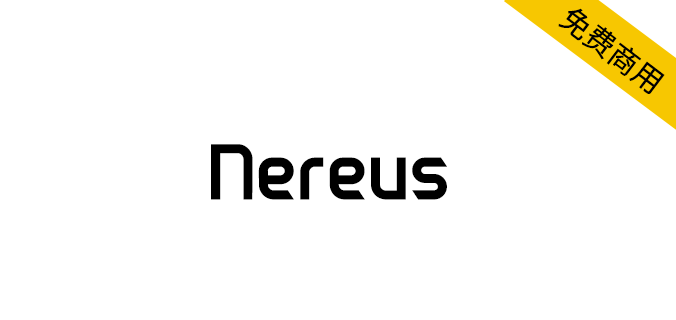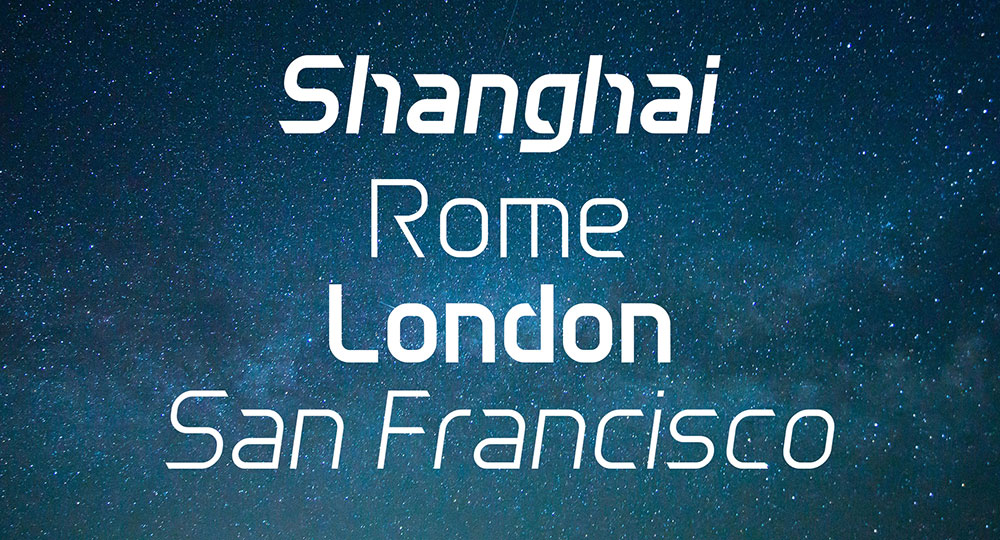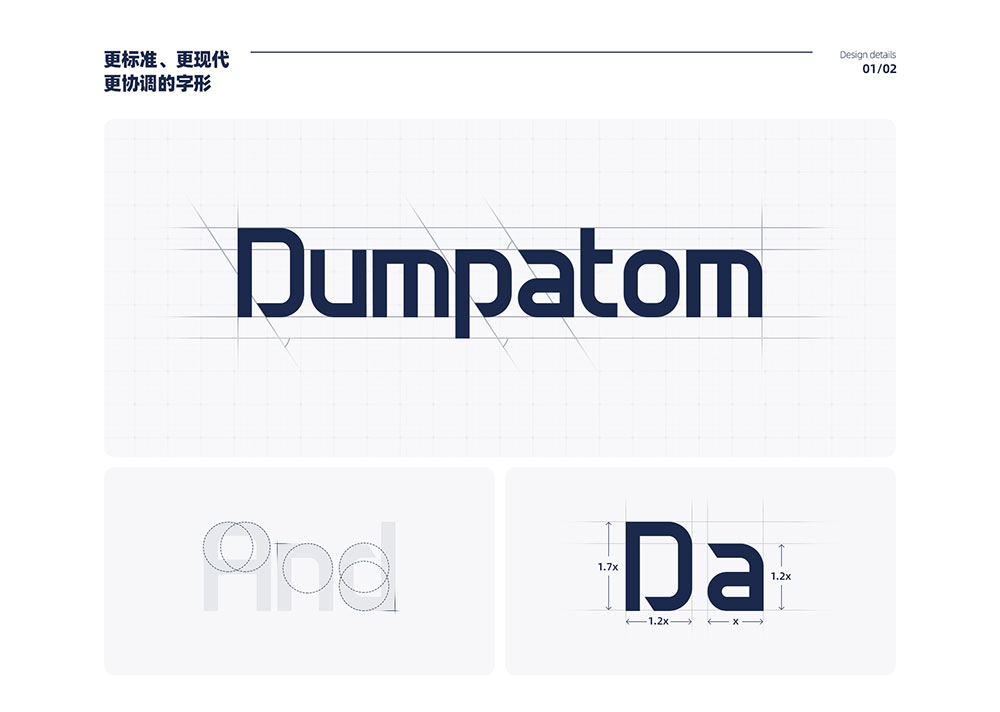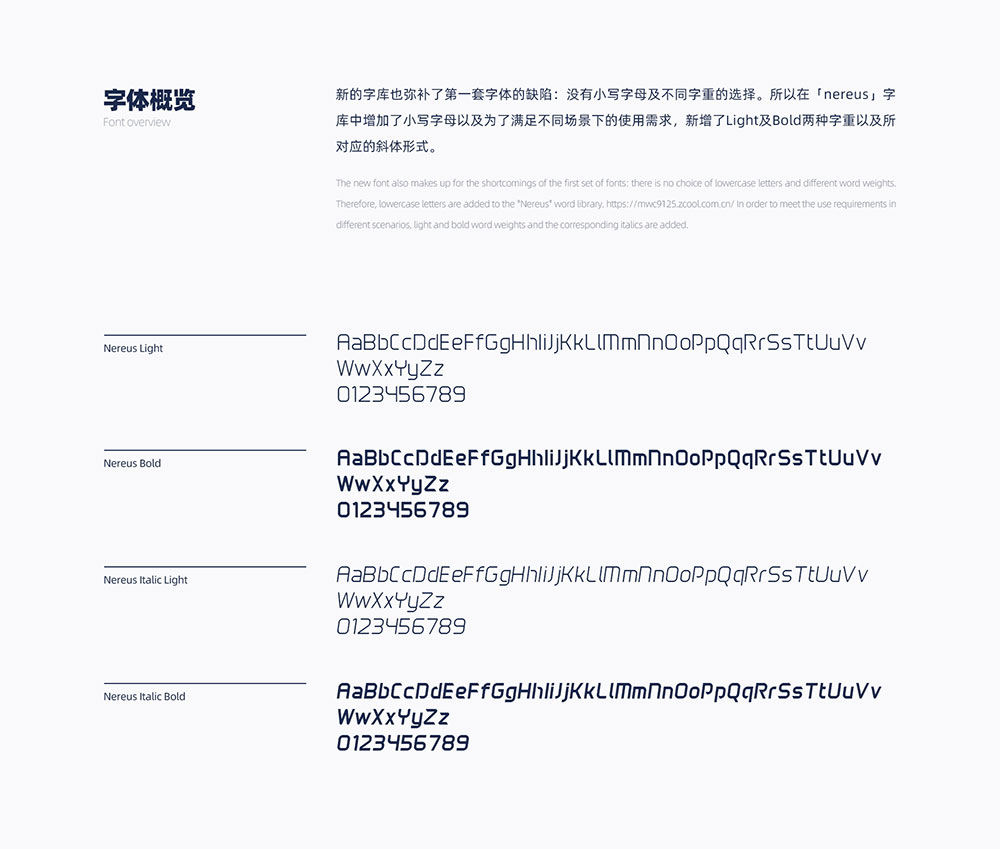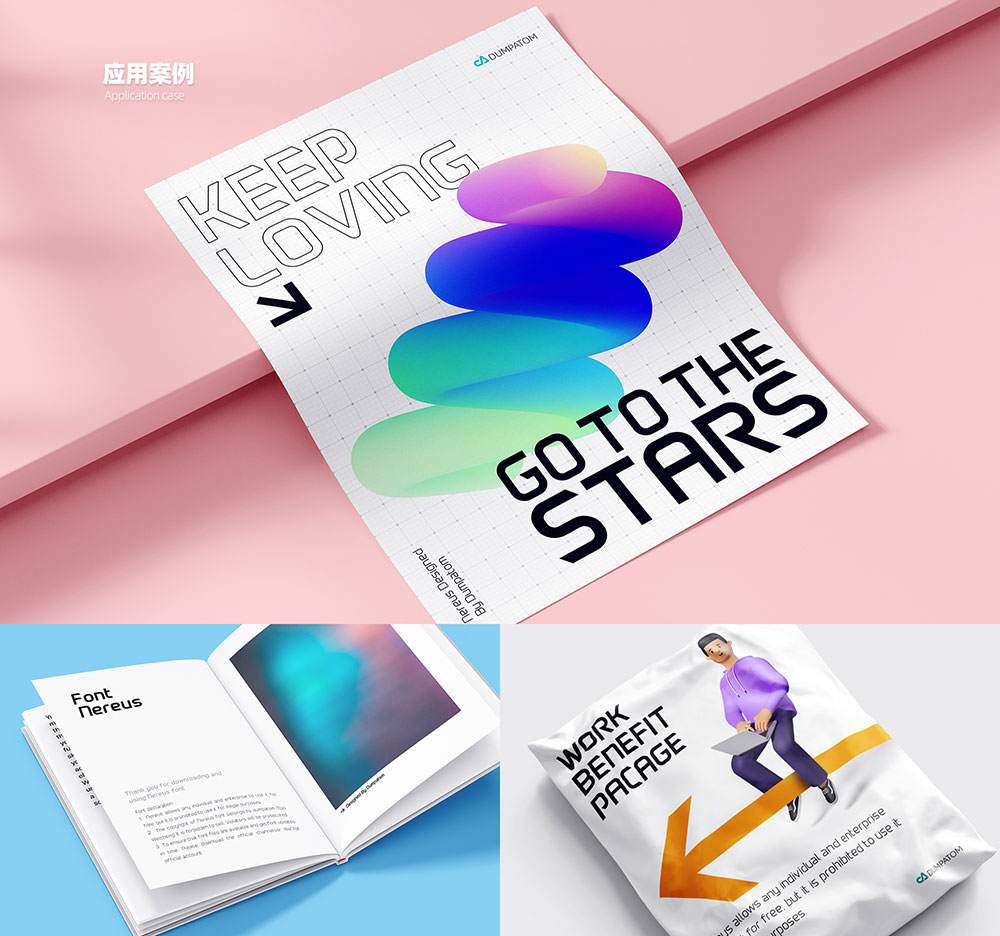
2020年9月初,在朋友的技术支持下,我于站酷平台首发了自己设计的英文字体包「EDIX」,上线一年多的时间内,获得了许多好评。
在一个全新的领域进行尝试并取得了还算不错的成绩之后,我没有停止继续探索的脚步。在经历了无数次的跌倒爬起后,终于能在今天提交一个满意的答卷:完全独立自主设计开发的第二套免费商用英文可变字体「Nereus」诞生了。—— 字体设计制作/动效设计/平面/包装:Dumpatom毛伟丞
项目背景:Nereus涅柔斯是希腊神话中的一个海神,他值得信赖、和蔼可亲、公正善良。也正是被他的人格品行所触动,所以希望能够再设计一款字体既继承之前字体的特性,又能在使用时更加的通用自如,最重要的是免费商用,为我所热爱的行业贡献自己的一点微薄之力。
设计语言探索:设计之初我构建了“Mtech”字族体系,希望能够再后续设计的字体中能够继承字族中时代前进的趋势以及现代至简的格调,同时也希望弥补缺憾,创造一个更加通用、赋予用户友好体验的好字体。
设计细节:在继承了“Mtech”字族的切角特征以及超前的未来感和现代感之外,新的字体设计更加的规范化、统一化。在设计制作的过程中制定项目完成重要节点,在完成目标日期前克服重重阻碍,不断的进行字体变化参数调整测试,最后凭借一己之力成功探索出了可变字体实现技术,产出了一套通用性极强的英文字库。